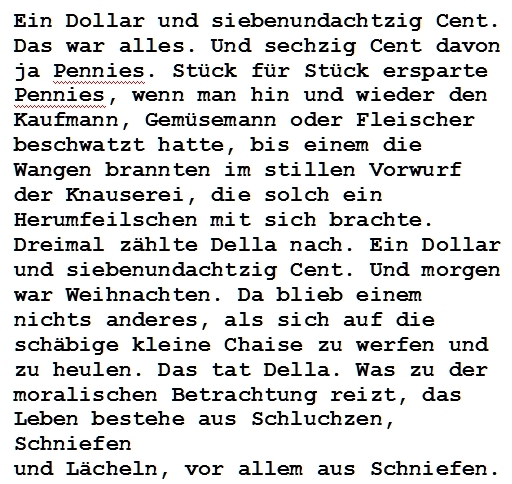
weiss vielleicht jemand welche Schriftart das auf dem Bild ist? Ich kriegs einfach nicht raus
möchte eine Wandschablone anfertigen.
Sieht aus wie die C64 8bit-Schrift.
Es ist ziemlich sicher eine Bitmap-Schrift und ich würde auf 8bit tippen. Welche genau das ist, so schwer zu sagen. Aber mein Favorit wäre der C64.
ummm, die Bildschirmschriften zu Anfang der 80er hab ich aber weitaus pixeliger in Erinnerung …
Ungefähr so:
Die Schrift des C64 war schon deutlich „rundlicher“ aber schon noch ein wenig gröber als das Gesuchte. Stimmt schon. Also ne 16bit font?
Schaut eigentlich wie eine ganz alltägliche COURIER Schreibmaschinenschrift
aus!LG